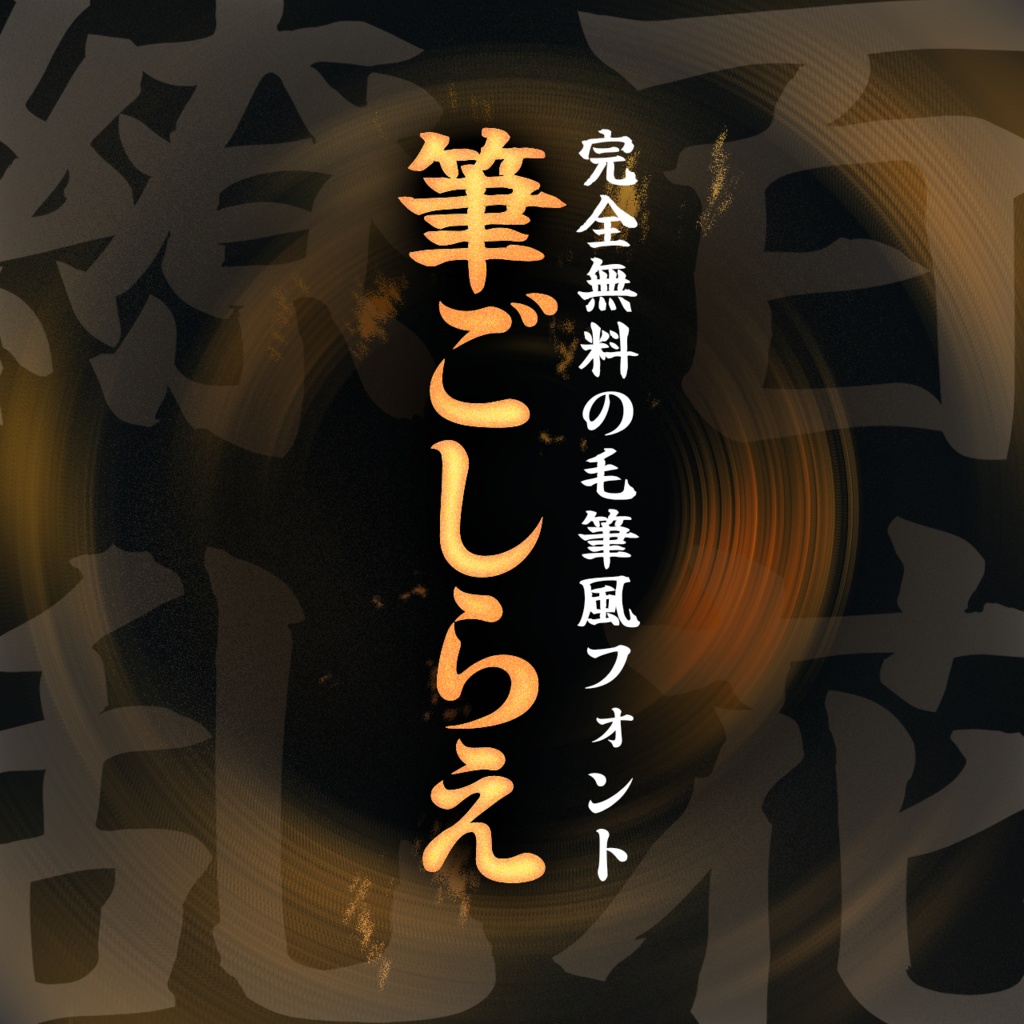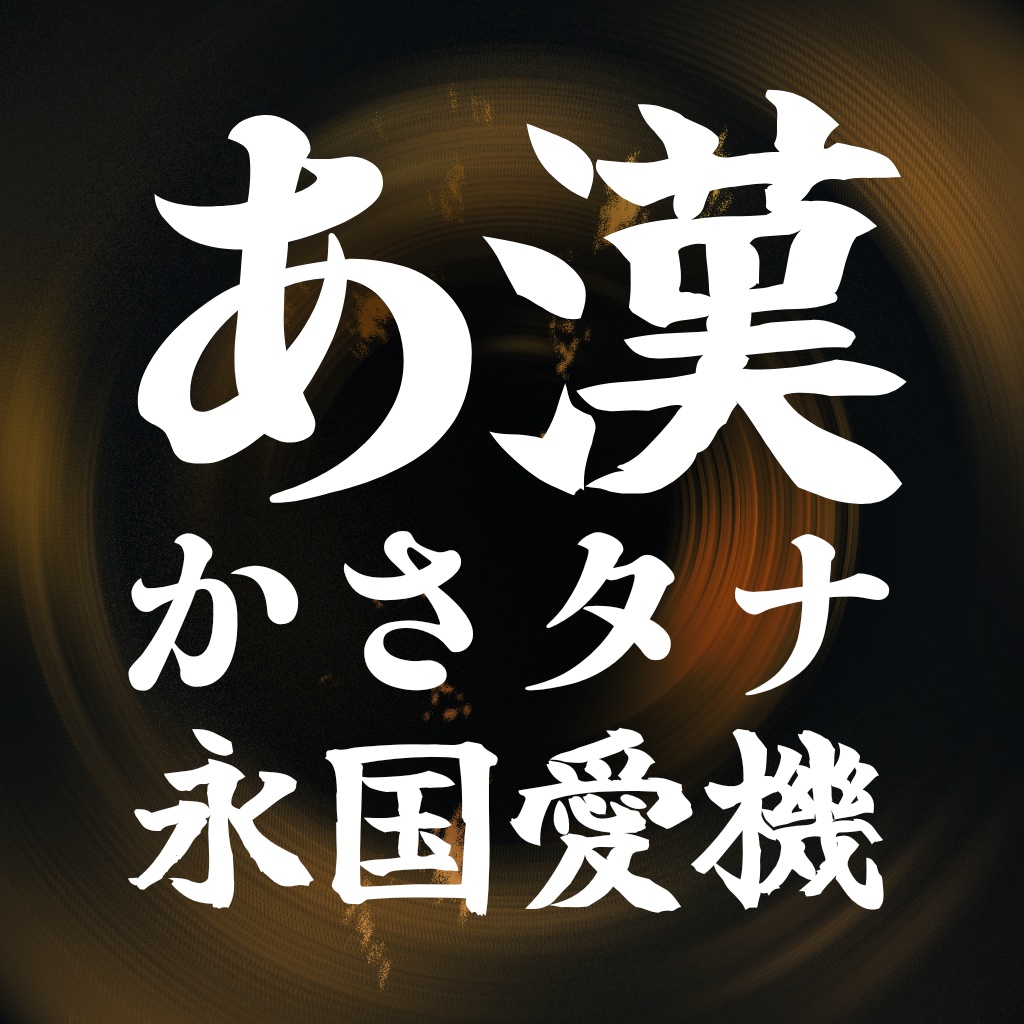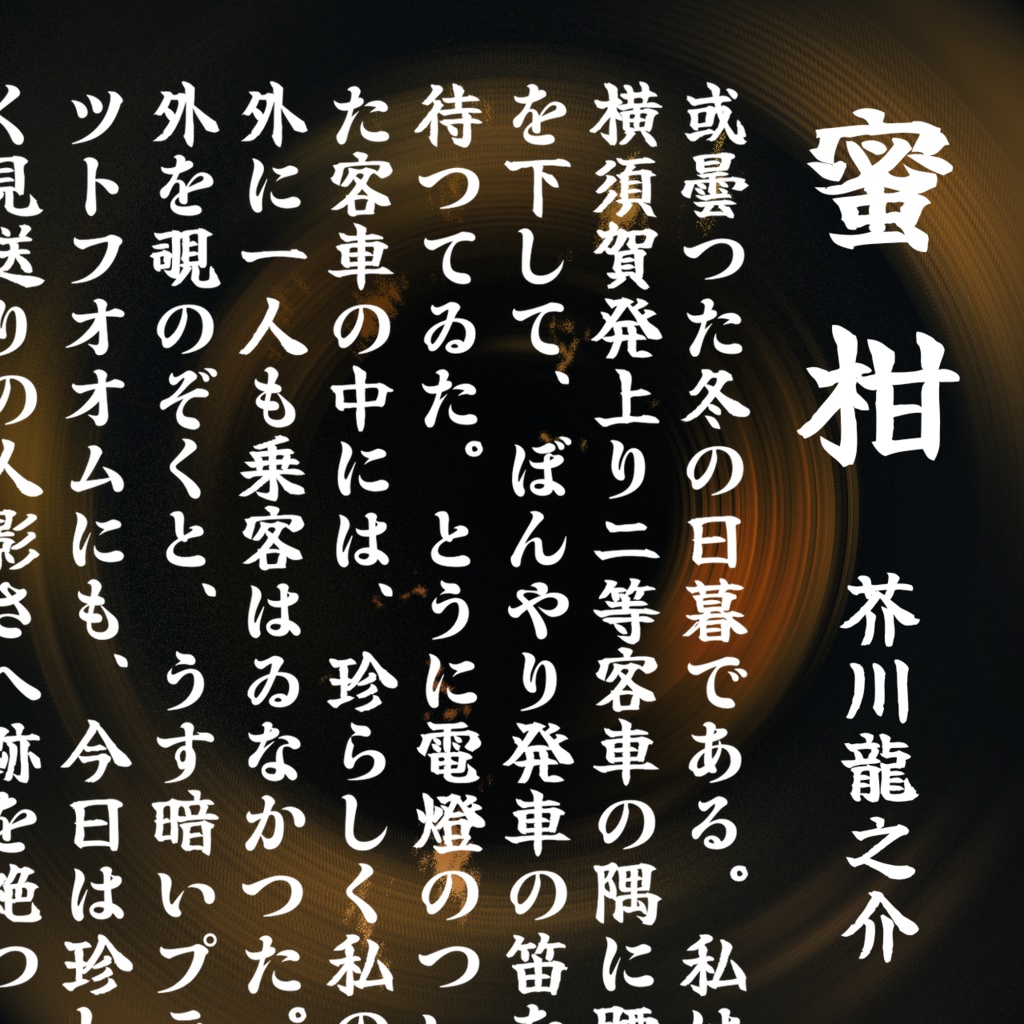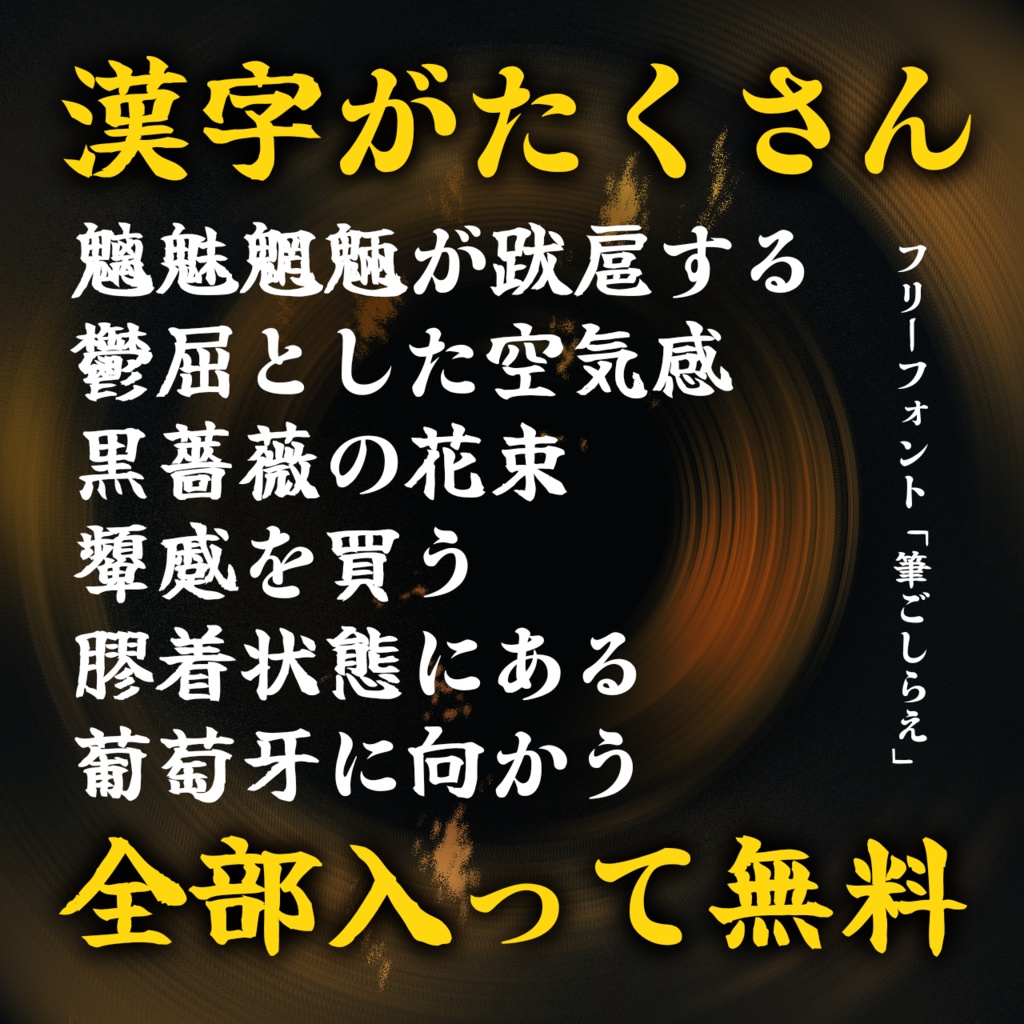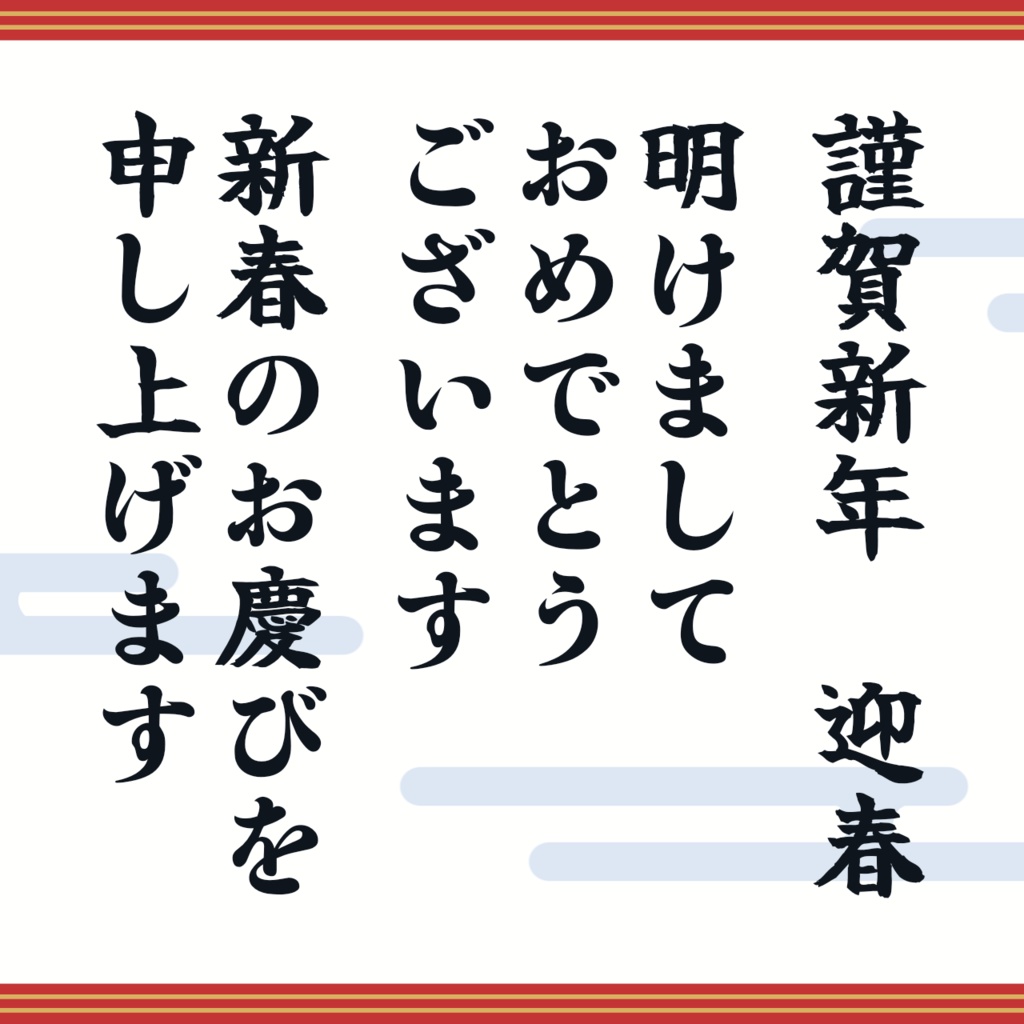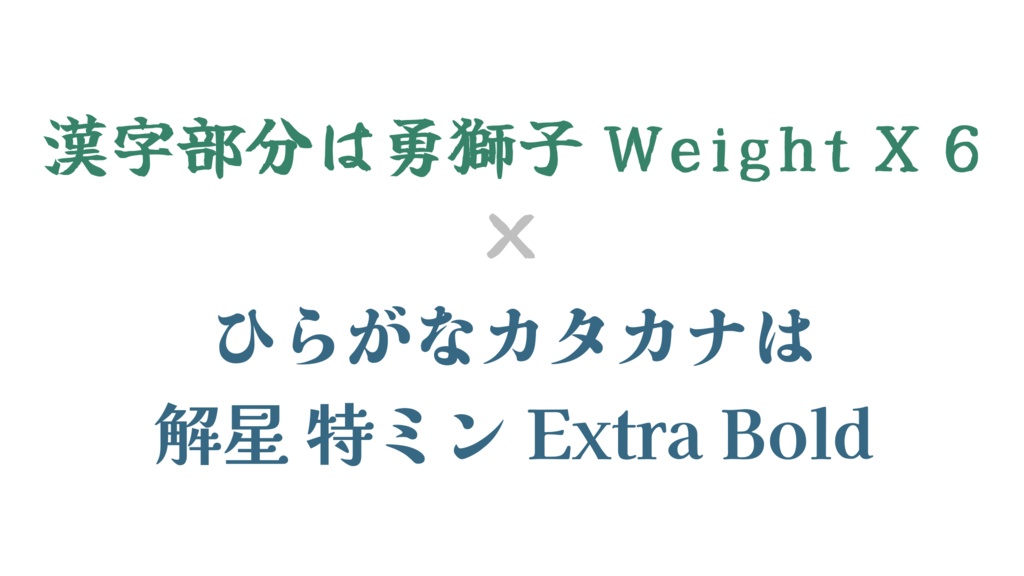
【フリーフォント】筆ごしらえ
完全フリーで太めの筆文字風フォントです。 結構な量の漢字が使えます。 商用利用もご自由に。 SIL Open Font License 1.1のもとで改変・再配布も可能です。 ■完全無料の筆文字風フォントで史上最大レベルの収録文字数 一般的なユースケースをほとんどカバーできる量の漢字を収録しています。太くてインパクトのある毛筆風の書体なので、年賀状などにもオススメです。 ■どこまでいっても〝完全無料〟 オープンソースのため、商用利用に関する制限や有料のフル版なども存在しません。最初からすべて無料で安心してお使いいただけます。 ※機械処理のため、一部字形にエラーが含まれている可能性があります。重要情報の記載や本文での使用は非推奨です。 スペシャルサンクス - 勇獅子 Weight X 6 - 解星 特ミン Extra Bold [2026.08.10]ver1.10 ライセンス表示および予約フォント名を整理し、OFL.txtなどの関連文書を同梱。フォント内部のライセンス情報と埋め込み設定も修正。また、ファイル形式をOTFからTTFに変更。